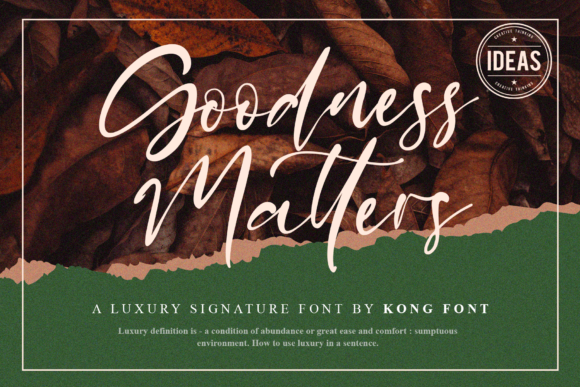
Goodness Matters
Si buscas recursos de alta calidad como Goodness Matters, este paquete premium es una opción fantástica para tus proyectos creativos.
Ya sea que estés creando productos POD (impresión bajo demanda), invitaciones de boda o gráficos para redes sociales, Goodness Matters es una opción ideal.